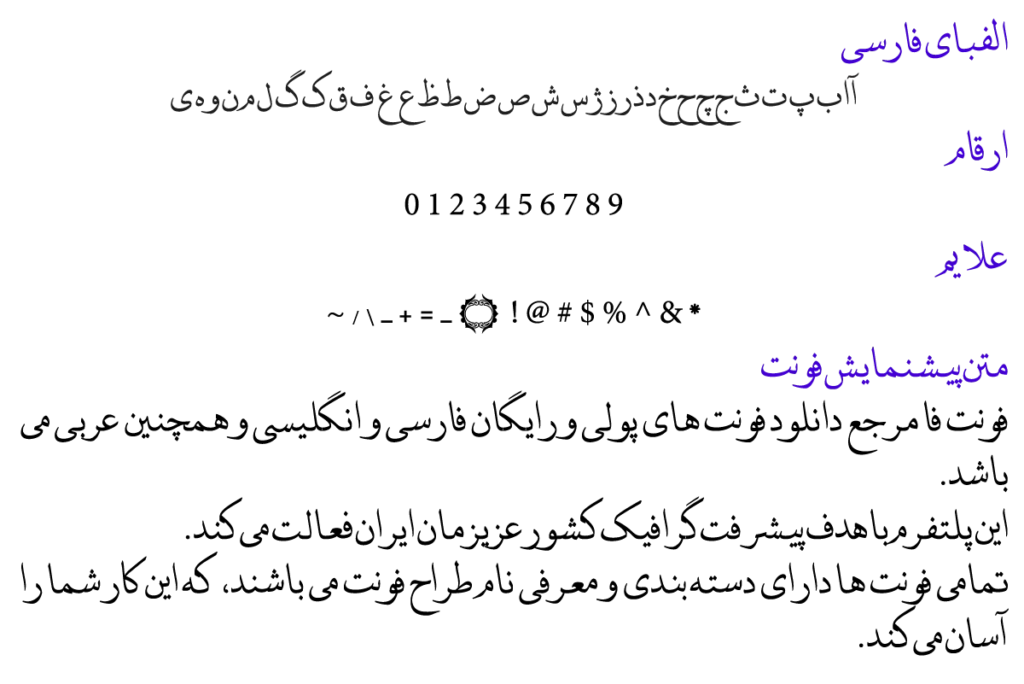
فونت فارسی نبی – Nabi
سال ساخت فونت: 1399
طراح فونت: حسین زاهدی نوع فونت: فونت خوشنویسی
پیشنمایش فونت نبی
توضیحات و معرفی فونت نبی
فونت فارسی نبی ( Nabi ) از مجموعه فونت های آزاد می باشد، و نیز نوع فونت خوشنویسی می باشد.
فونت خوشگل مربوط توسط حسین زاهدی در سال 1399 طراحی و ساخته شده است.
برای طراحی این تایپ فیس زیبا حدود یک سال زحمت کشده شده است.
این قلم زیبا از اعراب و کشیدگی پشتیبانی می کند که با Shift+J قبل از هر حرف اعمال می شود.
و نیز فونت در یک وزن معمولی است.
در تصویر زیر پیشنمایش این تایپ فیس را با شعر زیبای وطنم می توانید مشاهده کنید.